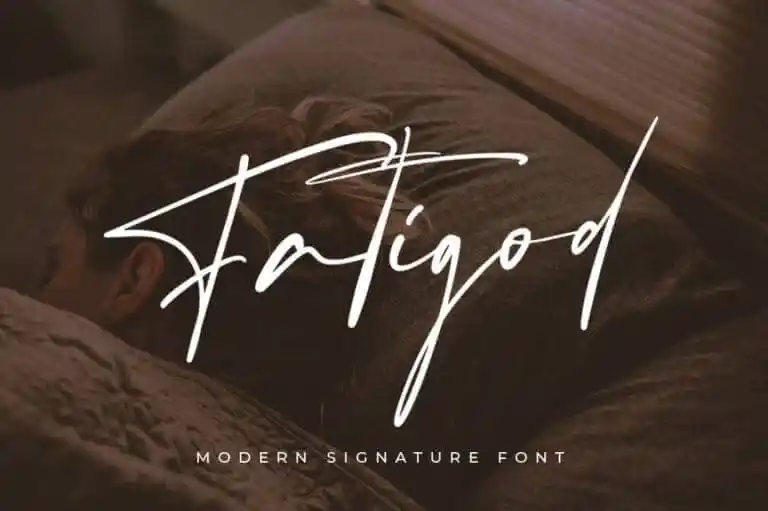
Fatigod Script Font – Download Grátis
A Fatigod Script Font é uma seleção cuidadosa de letras cursivas que transmite elegância sofisticada e luxo. Essa fonte foi criada pelo designer atemporal, a grandefonts, para aqueles projetos que buscam um toque autêntico. É ideal para uso em cartões de convidado de casamento, cartas de agradecimento, mensagens, cartões de boas-vindas e identidades empresariais. A fatigod font se destaca por sua linha fluida, alternativas atraentes e um espaçamento do tipo variável. Seu design elegante e flutuante criará um ar sofisticado em qualquer projeto que valorize uma mão-drita única e impecável. Tente ela no seu próximo design de cartão ou impressão digital para adicionar um toque único à sua marca.